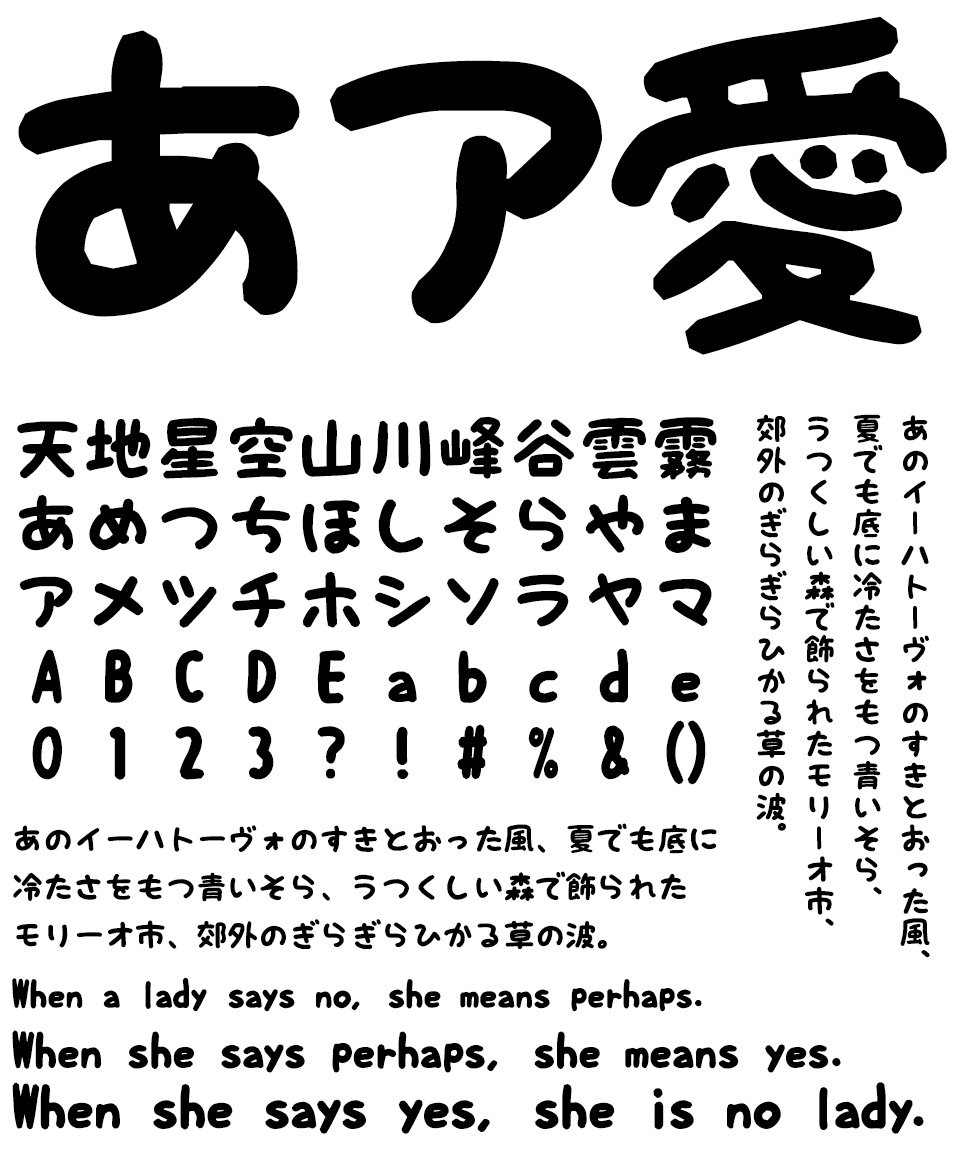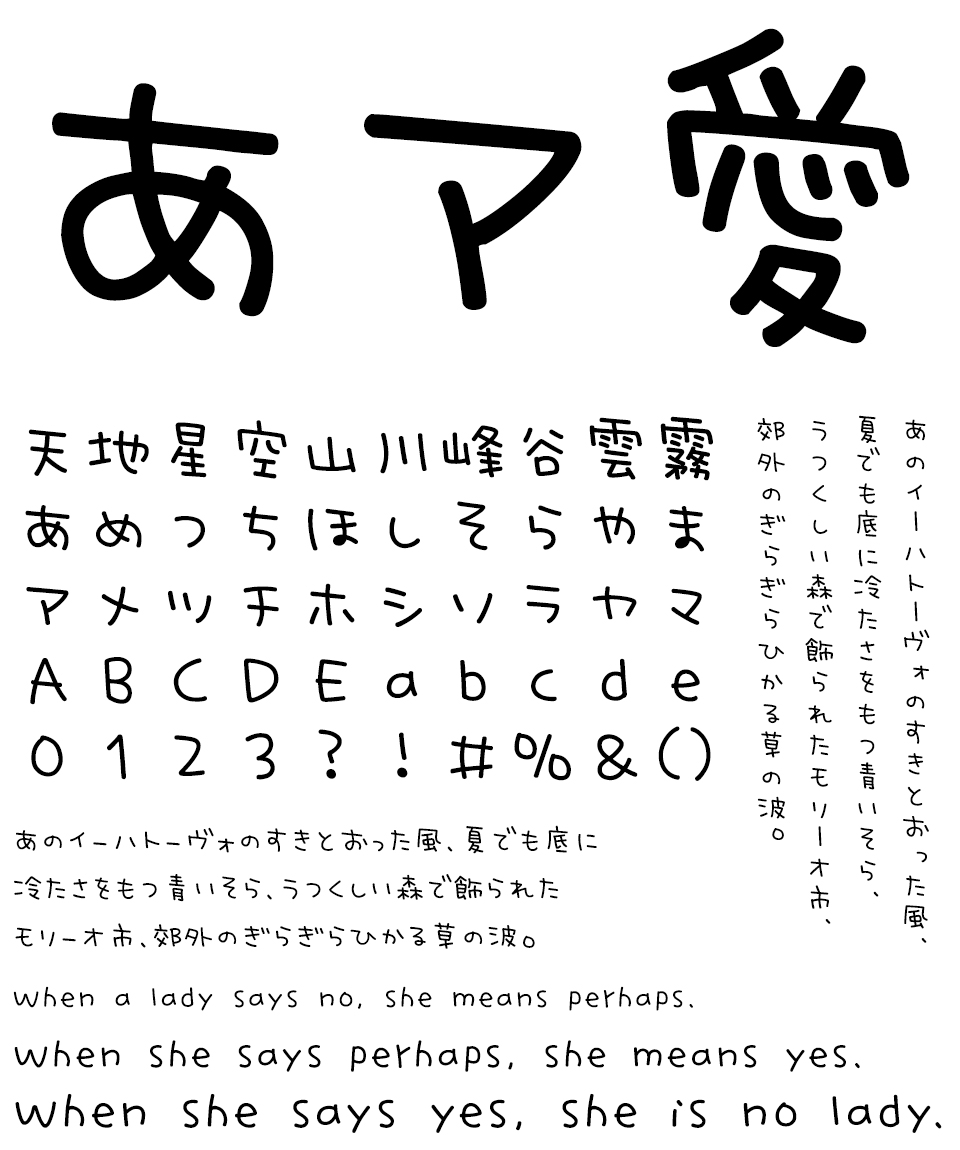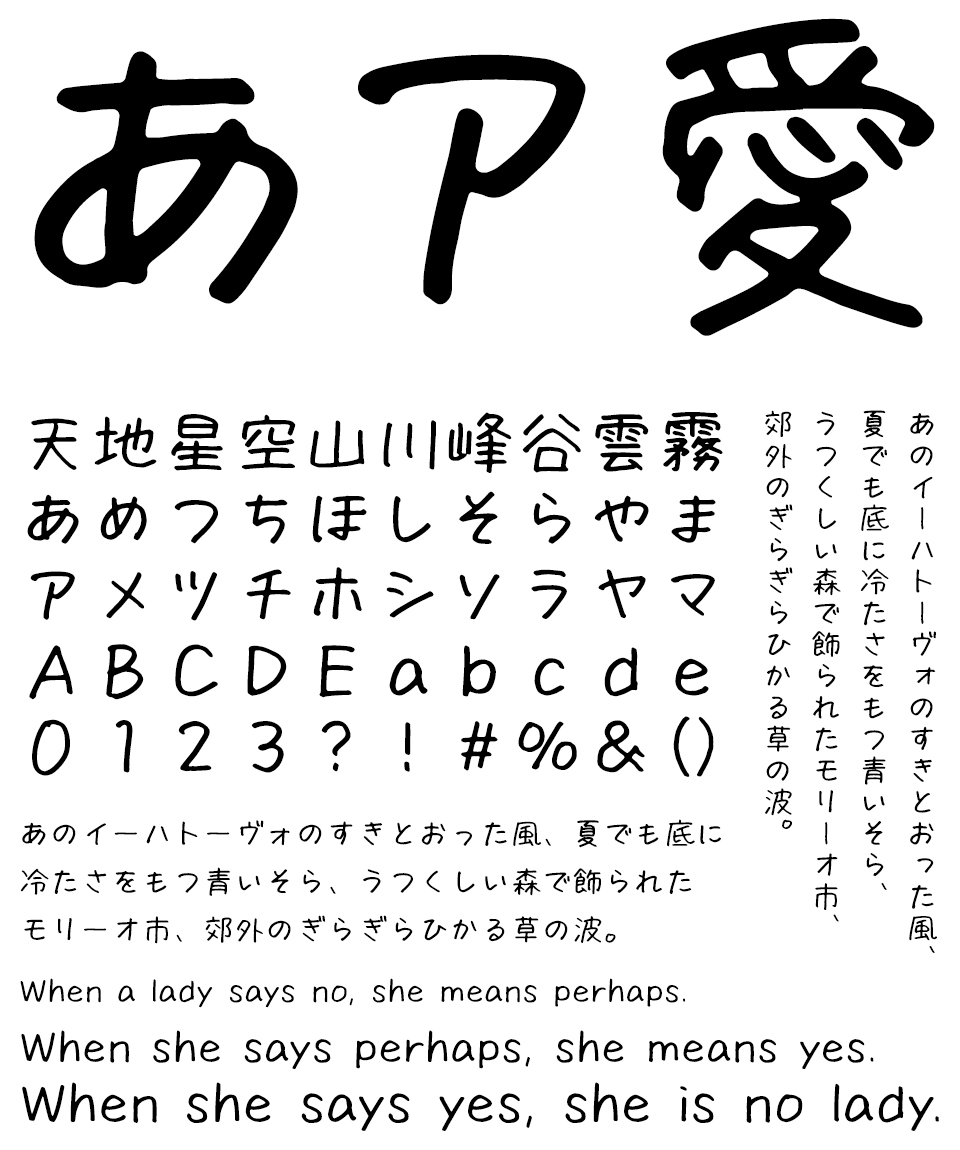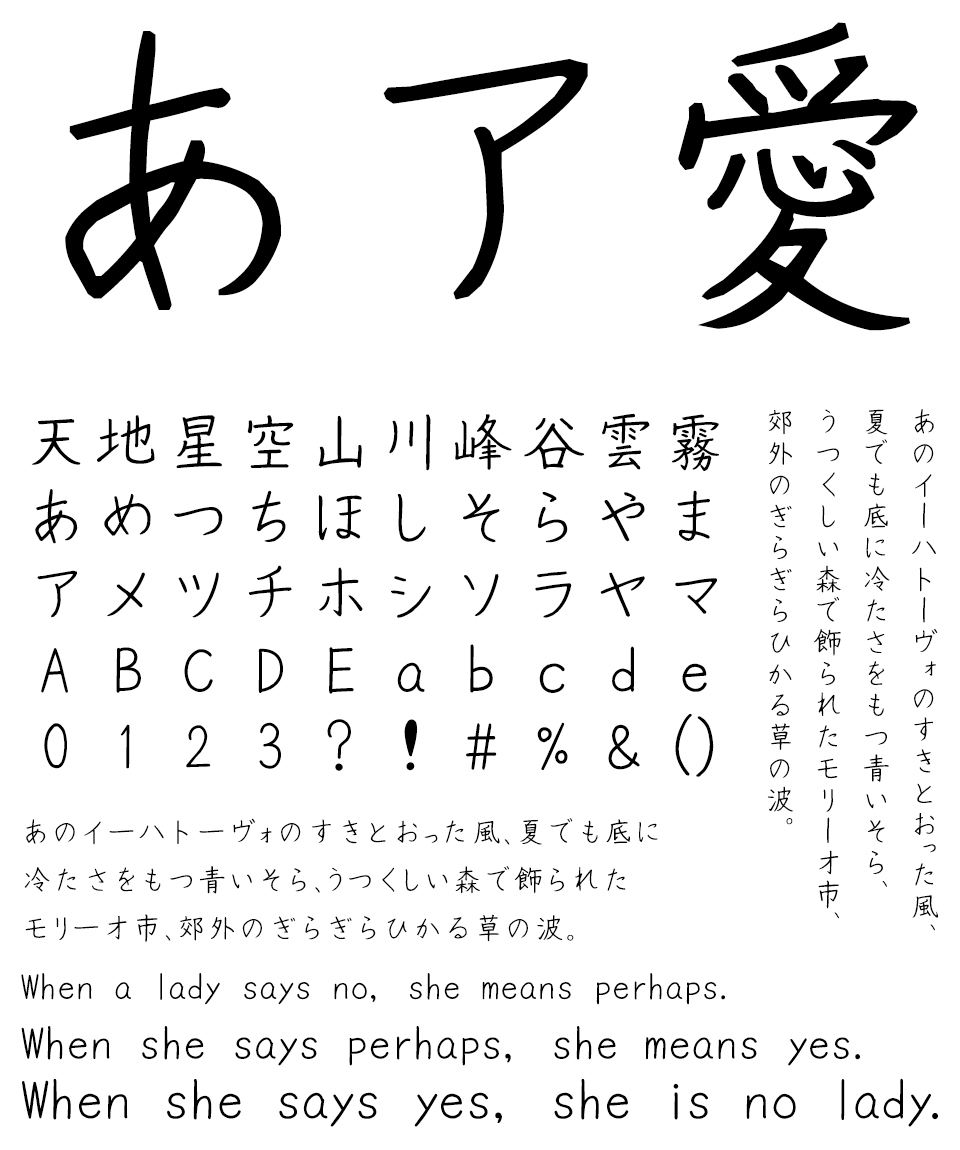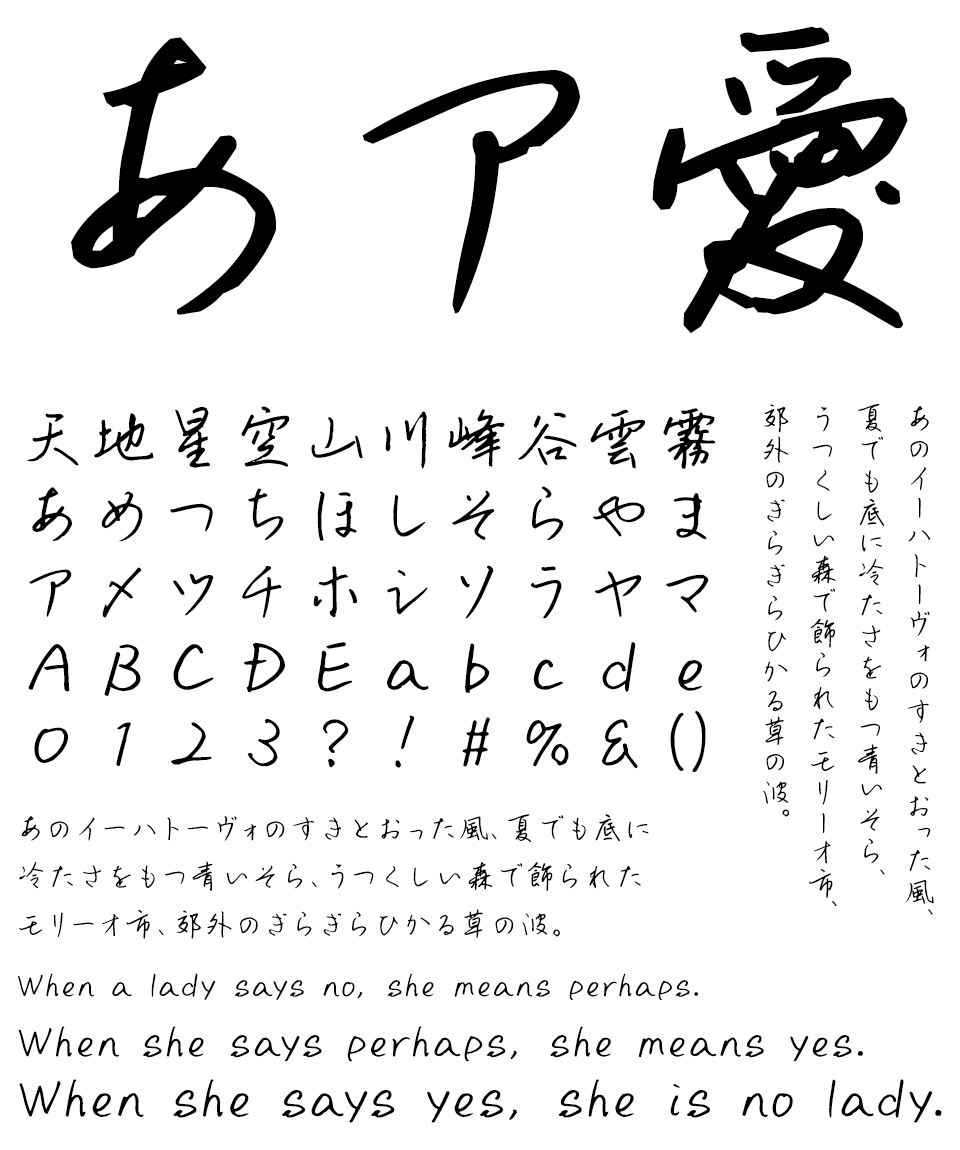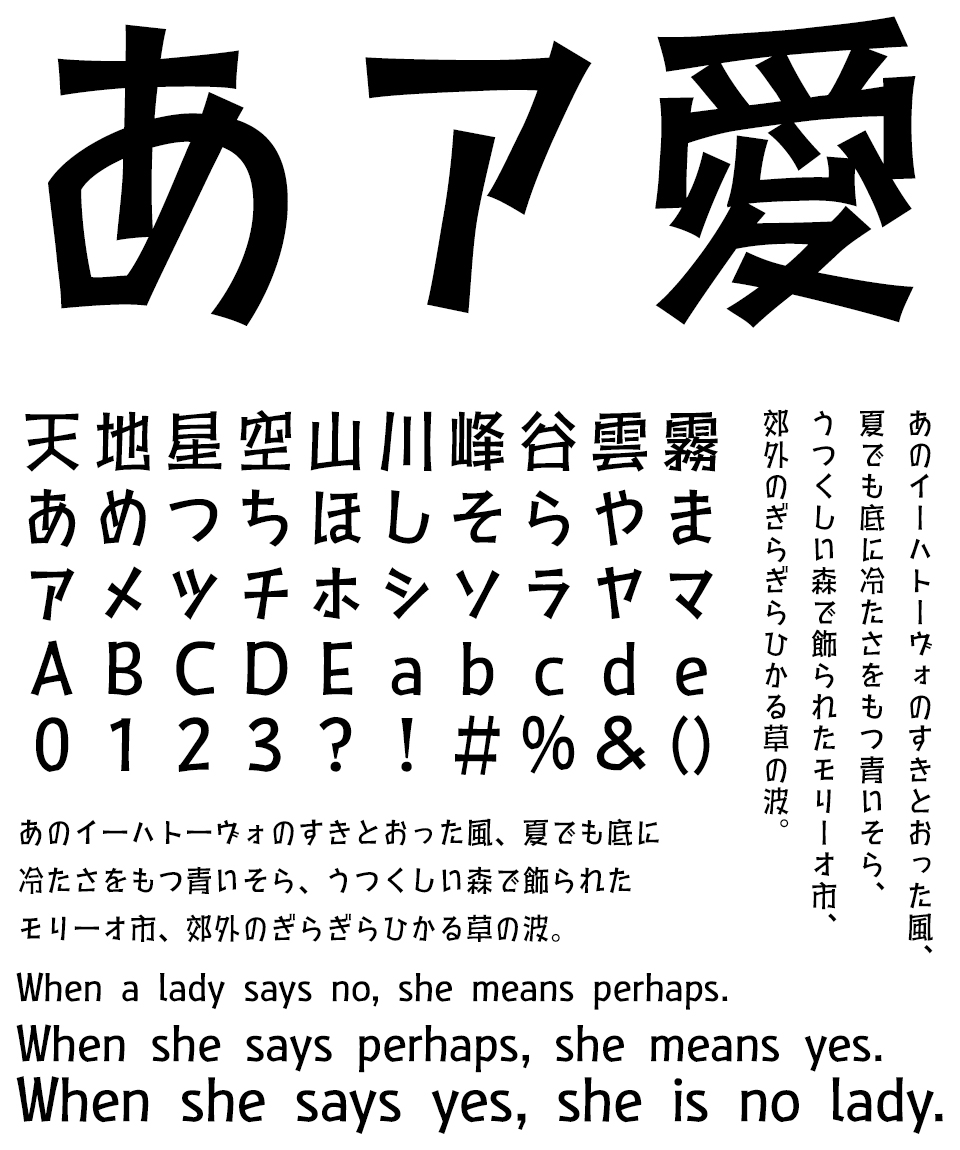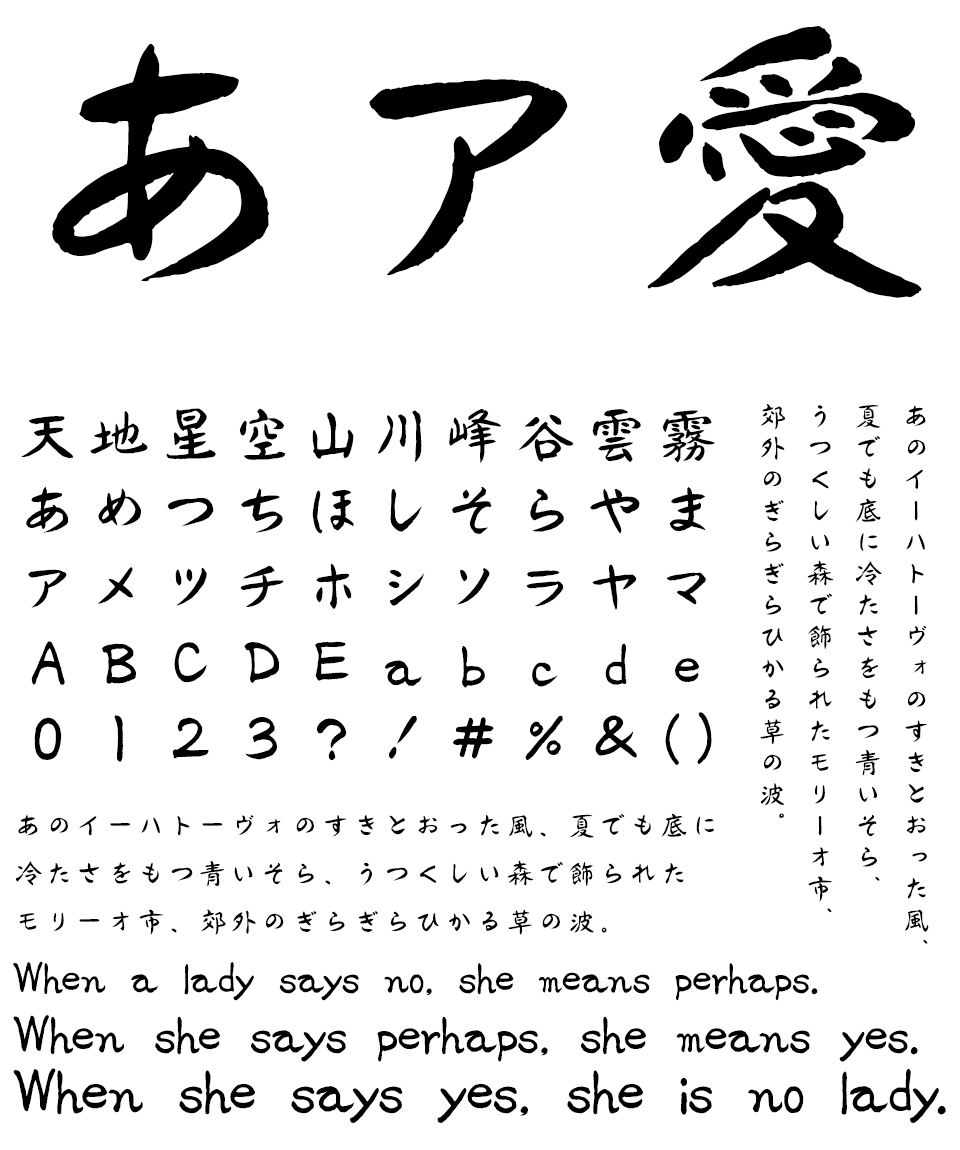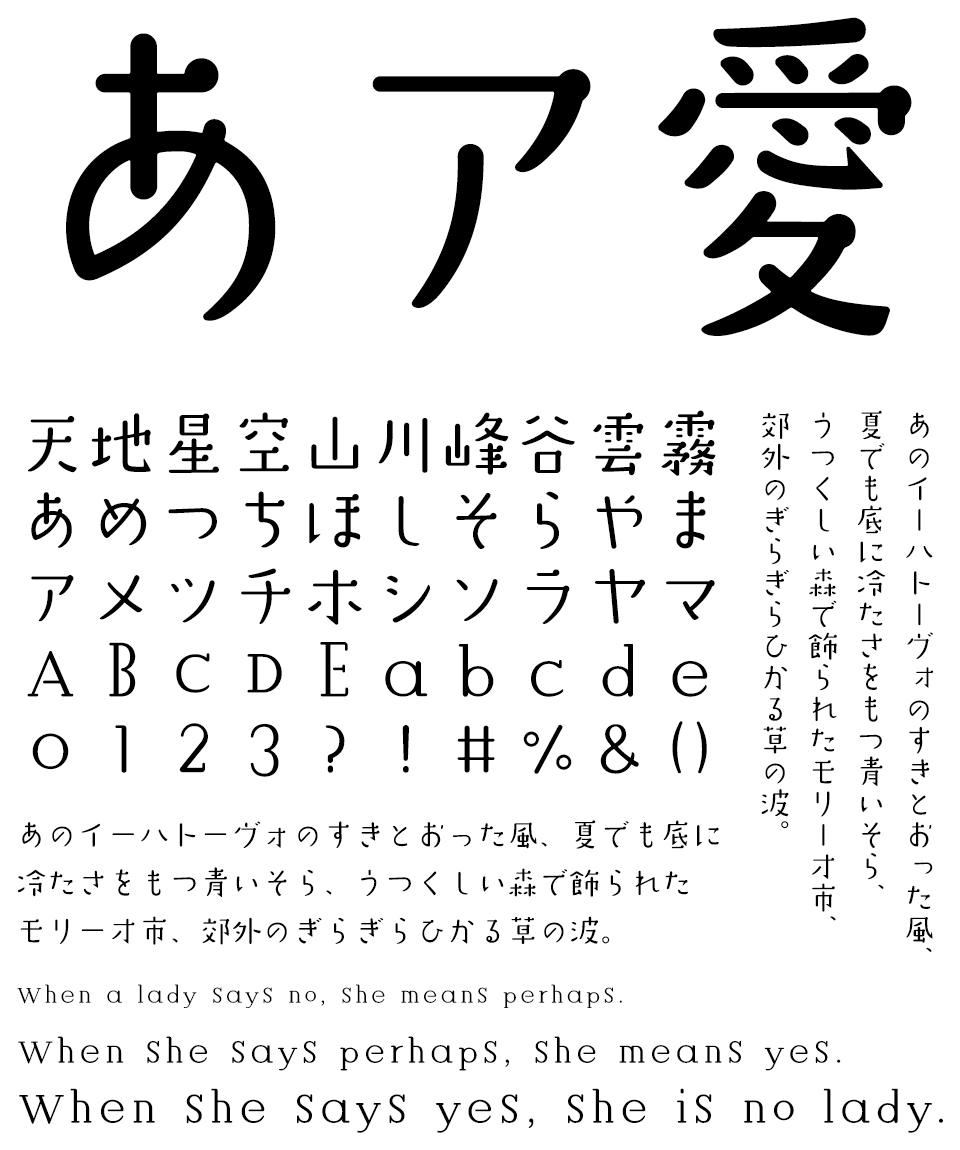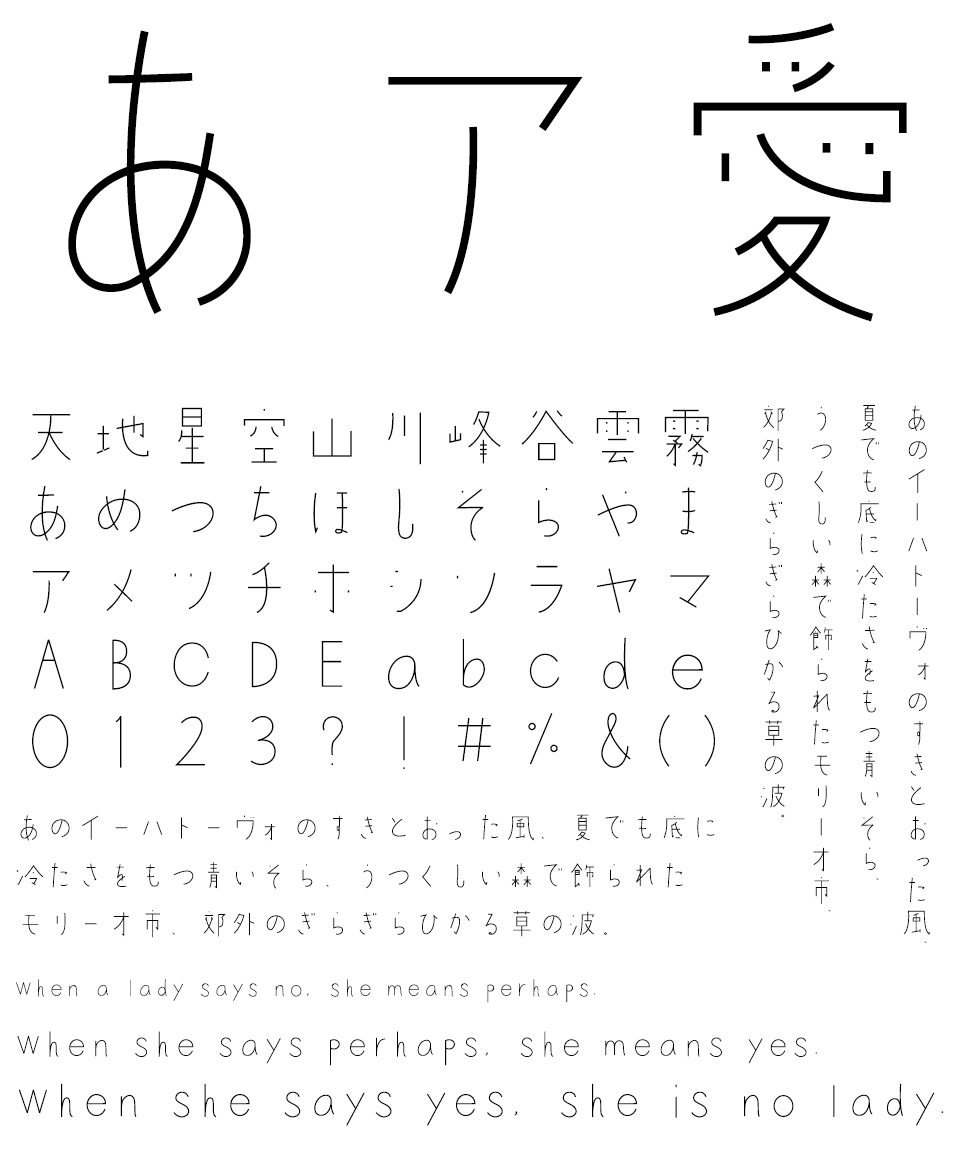
アナログ風・手書き風のクリエイティブデザインには、《親しみのある雰囲気を演出できる》《デジタルが主流の中で目立ちやすい》など、消費者に響きやすいメリットがあります。そのためBtoCの企業を中心によく見られるようになりました。
そんなアナログ風・手書き風のデザインに欠かせないのが、手作り感と温もりが伝わる手書きフォント。商品の特徴を説明するキャプションで使用するのにも適しますし、感情が伝わりやすい見た目の利点を活かし、お客様やスタッフからのコメントに使用するのも効果的です。
このページでは、いま注目の手書き系フォントを特集。デザインポケットで取り扱い中の商品からおすすめのフォントをご紹介します。SNSで話題になっている商品や定番のベストセラー、手頃な価格の商品など、厳選した40書体をご覧ください。
ご紹介するリアル手書き、手書き風フォント一覧
おすすめの手書きフォント 40書体
花とちょうちょ
SNSで話題沸騰中の大注目のフォントです。ペンで右上がりに書いた手書き文字から作った、ちょうちょのように軽やかな日本語フォントです。写真やイラストに書き込みをしたように傾けたレイアウトで使用するのもおすすめです。
空とひこうき
さらさらと流れる横へのつながり、インクのようなにじみを生かしたラフな手書きフォントです。写真やイラストに書き込みをしたように傾けたレイアウトで使用するのもおすすめです。
波とかもめ
しっかり太めのマーカーで描いたような手書き文字をベースに、弾むような伸び上がりや、脱力したような払いを入れて、リラックスした雰囲気を持った太め・丸め・ユーモアのある手書きフォントです。
ゆるねこ
絵文字・吹き出しがたっぷり収録されたゆる可愛い手書き風フォントです。 「ゆるねこ.ttf」「ゆるねこ-emoji.ttf」の2種類のフォントが収録されています。
まちのてちょう Regular/Bold
スマホひとつで気軽に手書きフォントが使えるように、iPadとApple Pencilを使って直筆で作成された手書きフォント。手書きだけど長文でも読みやすく、SNSでの情報発信などでも大活躍です。
まちのらくがき
サインペンで書いたゆるい手書き。それでいて長文でも読みやすい。そんなフォントを目指して作成しました。
アングル
手書きならではの大小のリズムを自然に表現できる、おしゃれなバリアブルフォント。カフェのメニューやSNS投稿、ブランドロゴ、写真に添えるひとことなど、大人っぽく洗練された手書き感を演出したいシーンにおすすめです。
TMミモザ L/R/B
まるで大人の女性の直筆ような手書き感たっぷり。細めのペンのにじみを残した、自然で穏やかな手書き文字です。